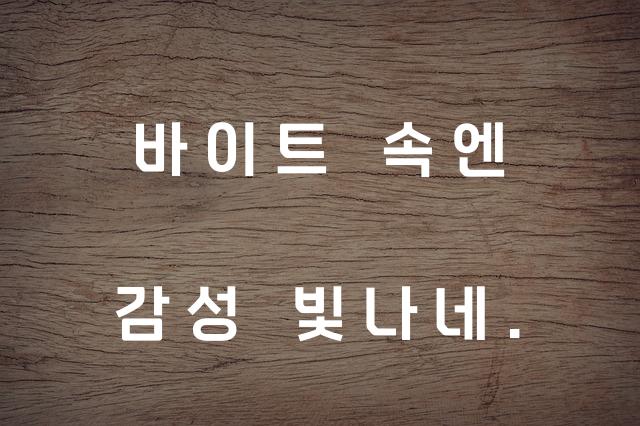
엘리스디지털배움체는 제목용으로 디자인된 꽉 찬 고딕 스타일의 폰트입니다. 디지털 환경에 최적화되어 강렬하고 선명한 인상을 주며, 부드러운 곡선이 특징입니다.
엘리스디지털배움체은(는)
기본 고딕, 픽셀/코딩, 굵은 고딕, 게임 느낌, 단단함, 복실복실, 길고/크고 계열의 생김새를 가지고 있으며
교육 자료, 어린이 책, 보고서/문서 등에서 자주 활용되며, 효과적인 메시지 전달에 적합합니다.
이 폰트는 교육, 출판/미디어, 유아/가족 분야에 잘 어울리며,
친근한, 부드러운, 편안한 느낌을 담고 있는 것이 특징입니다.